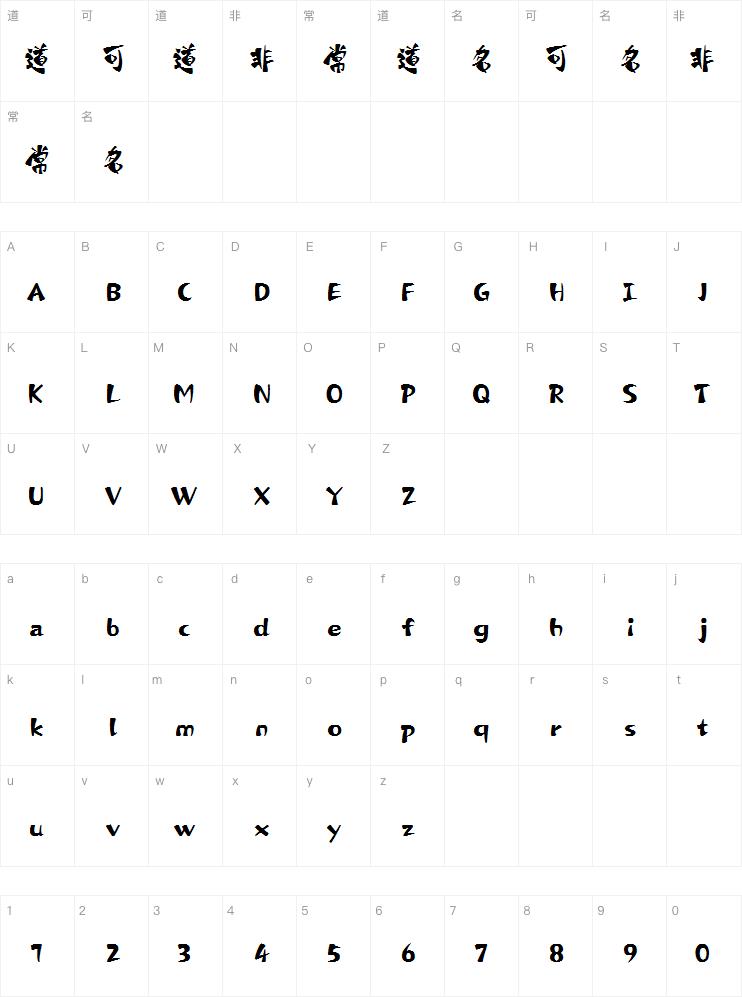
山海花语w
山海花语,是一款全新的字体,包含汉字9169个,符号200+个。该字体是一款卡通风字体,该字体字形灵动多变,童趣可爱,同时融入手写风笔势,结构多变灵动,字形活泼清新,造型生动有趣,具有灵活的适用性,天真俏皮又不失时尚感。该字体字形随笔画多少、结构布局不同而大小不一,各个字的大小随字形的不同而呈现不同的大小,但是在变化中寻求平衡,使得整个字体更具有手写感的温度和节奏感,整体笔触圆润,灵动笔画贯穿笔画始终,内涵丰富,弧度柔和,撇笔平缓舒展,尽显俏皮灵动。